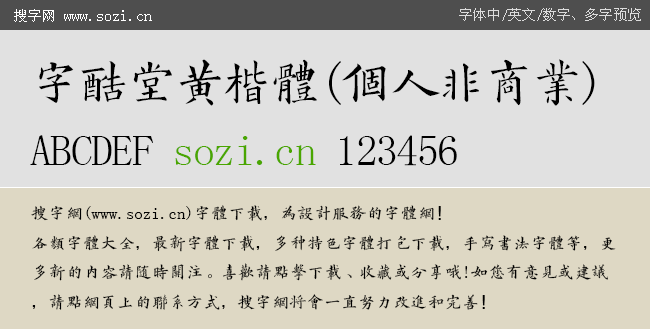
字酷堂黃楷體(個人非商業(yè))
搜字網(wǎng)提供一款字酷堂黃楷體(個人非商業(yè))中文書法字體下載字酷堂黃楷字體是一款手寫風(fēng)格的楷體字體,形體端秀而骨架勁挺,適合應(yīng)用于廣告設(shè)計、名片設(shè)計、包裝印刷、兒童產(chǎn)品設(shè)計等應(yīng)用。